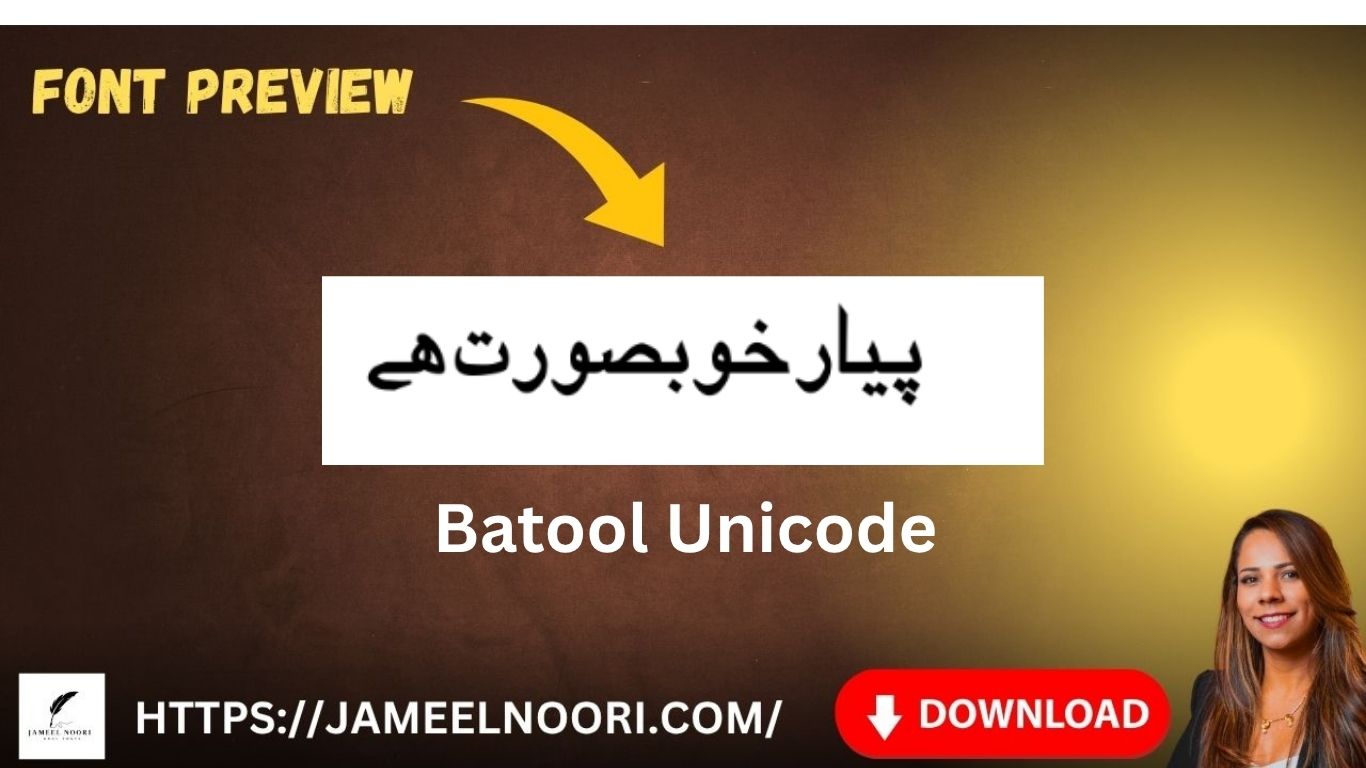
Introduction – Download Urdu Font Batool Unicode
Agar aap Urdu typing aur designing ke shaukeen hain, to aapko Download Urdu Font Batool Unicode zarur try karna chahiye. Yeh aik mashhoor Urdu font hai jo Unicode standard ke mutabiq hai aur kai Urdu software aur web applications mein use hota hai.
What is Download Urdu Font Batool Unicode?
Download Urdu Font Batool Unicode aik Urdu TrueType Font hai jo specially un logon ke liye design kiya gaya hai jo Urdu mein Unicode ke zariye likhna pasand karte hain. Is font ko aise design kiya gaya hai ke yeh har platform par asani se kaam karta hai, chahe aap Windows, macOS ya Android use kar rahe hon.
Features of Batool Unicode
✅ Unicode compliant
✅ Stylish aur readable Nastaleeq style
✅ Web aur print dono ke liye best choice
Benefits of Using Download Urdu Font Batool Unicode
- Unicode support ki wajah se compatibility ka masla nahi hota.
- Achi readability aur elegant style.
- Urdu lovers ke liye perfect font.
Conclusion – Download Urdu Font Batool Unicode
Agar aap Urdu mein likhne aur design karne ka shauq rakhte hain to Batool Unicode font aap ke liye aik behtareen choice hai. Yeh font na sirf asan hai install karna, balke iska Unicode support isay modern applications mein bhi reliable banata hai.
Is it suitable for professional graphic design?
Yes, it has clean curves and quality rendering.
What makes Batool Unicode different from other fonts?
It’s lightweight, Unicode-supported, and highly readable.